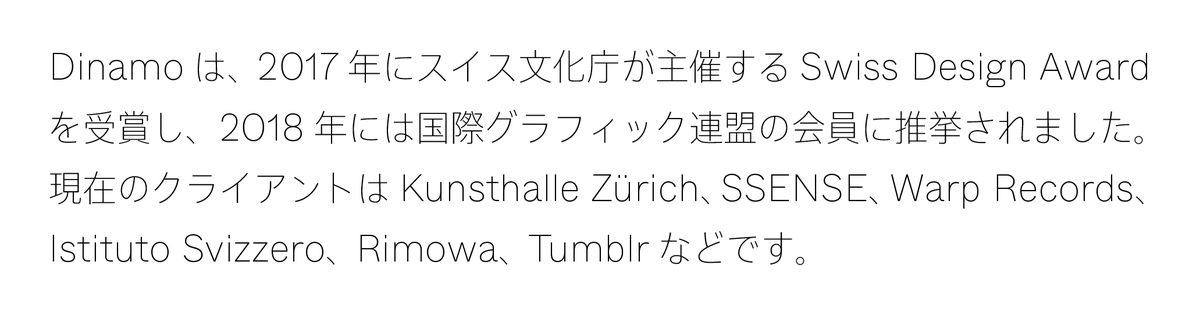
フィットフォントサービスの欧文フォントに、Dinamoの3ファミリーを追加
タイププロジェクトは2020年5月21日に、フィットフォントサービスに、スイスのタイプデザインスタジオDinamoの欧文フォントを追加したことを発表した。
Dinamoは、バーゼルとベルリンに拠点を置くタイプデザインスタジオで、リテールフォントの販売に加え、Kunsthalle Zurich、SSENSE、Warp Records、Istituto Svizzero、Rimowa、Tumblrなどのクライアント企業に、カスタマイズフォントやコンサルティングを提供している。
フィットフォントは、タイププロジェクトのサイトのスライドバーによりウエイトや字幅を調整することで、モニタのサイズやディスプレイの解像度、広告やカタログなど使用目的に合わせた最適なフォントを注文できるサービス。独自開発技術により、ウエイトやコントラスト、字幅を変更した場合でも、字画の比率が適正で常にバランスの取れた状態を保ち、ダイナミックに変化しながらもデザインの一貫性と品質を保持することを実現している。
フィットフォントサービスに追加したDinamoの欧文フォントは、Monument Grotesk、Whyte、Laicaの3ファミリーで、全16フォント。
Dinamoの創業者であるJohannes Breyer氏とFabian Harb氏は、「私たちは、フォントの枠を超えたいろいろなことに興味を持っています。フィットフォントによって、日本や西洋のデザイナーやブランドは、文字によるメッセージをより手軽に多言語で展開できるようになります。私たちは、このクロスカルチャーなコラボレーションに大いに期待しており、タイププロジェクトのフォントが、フィットフォント欧文パートナーのフォントと一体となって可能性を広げていくことを楽しみにしています。」とコメントしている。
▼組合せ例:Dinamo Whyte Thin + TPスカイフィットフォント
タイププロジェクトでは、企業のメッセージを伝えるための手段としてフォントによるブランディングを提案している。フィットフォント技術を用いて、市販されていないウエイトや、欧文組替え、オリジナルのひらがなやカタカナを開発するなど、世界有数のグローバル企業にコーポレートフォントを提供している。